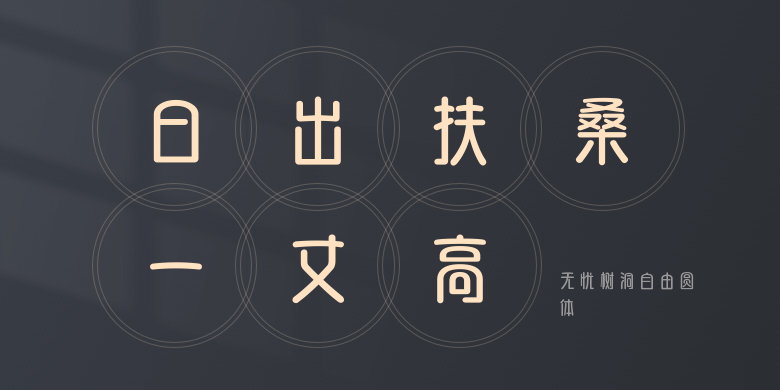
无忧树洞自由圆体
无忧树洞自由圆体,这款字体结构工整、笔画清晰,兼顾美观与易读性,适用于标题、正文、海报、包装、LOGO 等多种场景。字形优雅稳定,风格百搭耐看,适配日常排版与创意设计,让文字呈现更舒适、更具质感。无忧树洞自由圆体一笔一画,皆是细节,以均衡的比例、流畅的线条打造舒适视觉体验,字形端正大气,风格简约现代。无论是商业设计、品牌宣传还是日常排版,都能轻松驾驭,让文字更有格调与力量。无忧树洞自由圆体字体下载。